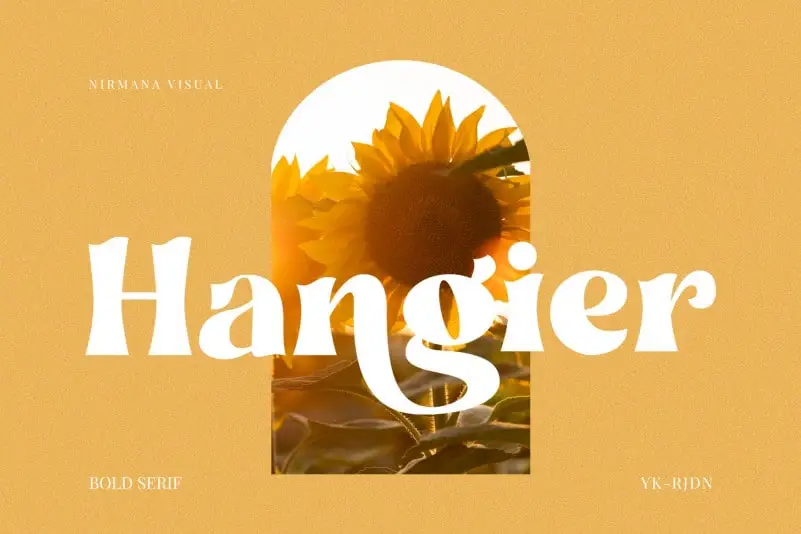
Hangier Serif Font – Download Grátis
A Hangier Serif Font é uma elegante tipografia serifada criada pelo designer Nirmana Visual – Sigit, com a intenção de oferecer uma fonte de alta qualidade e classe para atender todas as necessidades do design. Inspirado no gosto contemporâneo pelos estilos mais sofisticados, essa fonte foi projetada para ser versátil, atendendo perfeitamente tanto aos projetos grandes quanto aos detalhes menores. Perfeita para adicionar um toque de elegância e classe a qualquer projeto, seja em layouts de jornais, sites corporativos ou capas de livros, esta fonte é uma escolha ideal para designers que valorizam sofisticação e estética contemporânea na sua obra.